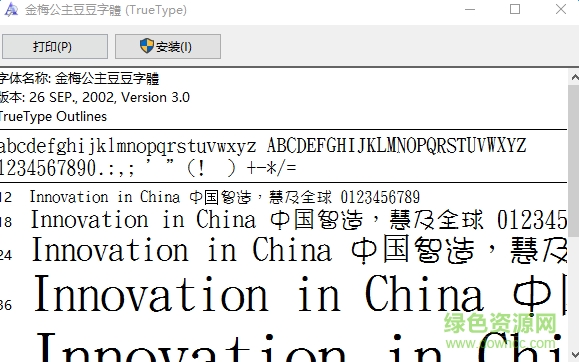
金梅公主豆豆字體是一款很實(shí)用電腦字體,看名字就應(yīng)該知道這款字體肯定是很淑女、很有特點(diǎn)字體,活潑可愛(ài),可以用于很多方面,不管是藝術(shù)設(shè)計(jì)還是寫作題詞都是很不錯(cuò)的,歡迎有需要的朋友來(lái)綠色資源網(wǎng)下載。
金梅公主豆豆字體是真的很好用哦,用來(lái)p圖,在圖片上寫字也是很好看的,大家也可以下載試試哦。